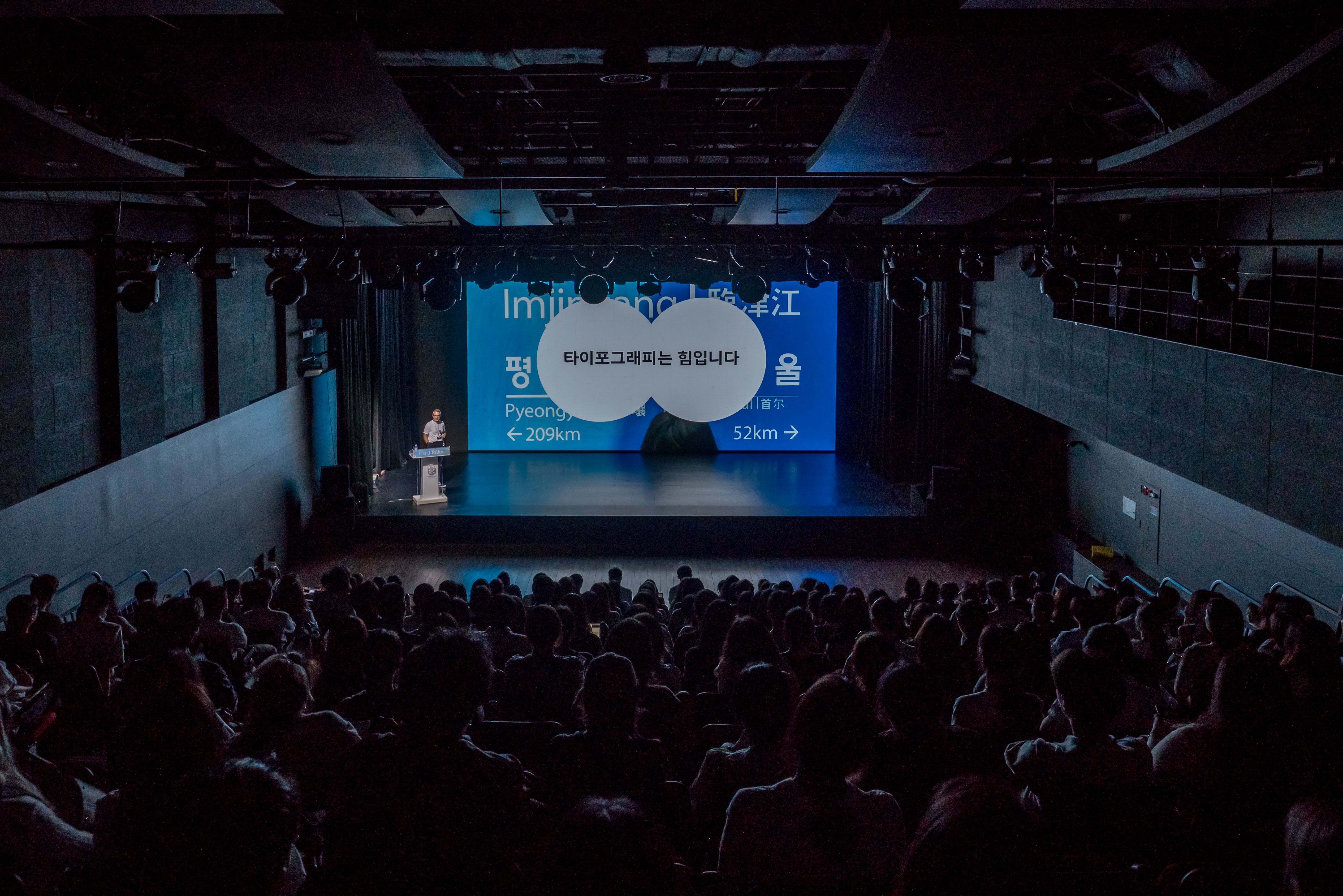
글로벌 폰트 디자인 및 기술 선도 기업 모노타입(Monotype)이 주최한 브랜드톡 코리아 2025(Brand Talks Korea 2025)가 성황리에 막을 내렸다. 7월 31일 서울 가빈아트홀에서 열린 이번 행사는 300명 이상이 참석했으며, 국내외 다양한 업계의 디자이너, 마케터, 브랜드 전략가들이 한자리에 모여 높은 관심과 뜨거운 반응을 이끌어냈다. 이번 행사는 단순한 세미나를 넘어, 브랜드와 타이포그래피의 전략적 가치에 대해 논의하고 인사이트를 공유하는 장이었으며, 국내 타이포그래피 및 브랜딩 분야를 대표하는 전문 세미나로서의 입지를 확고히 했다.
이날 무대에는 세 명의 연사가 올라 브랜드 전략과 경험 설계, 문화적 정체성 구축에 있어 타이포그래피가 어떤 역할을 하는지를 다양한 시각에서 조명했다.
고바야시 아키라(Akira Kobayashi) 모노타입 크리에이티브 타입 디렉터는 40년 가까운 경력을 지닌 세계적인 서체 디자이너로, 독일의 서체 디자이너 헤르만 차프(Hermann Zapf)와 스위스의 아드리안 프루티거(Adrian Frutiger)와의 협업으로도 잘 알려져 있다. 오랜만에 한국을 찾은 그는 글자 형태 자체가 메시지를 전달하는 힘을 다양한 브랜드 사례를 통해 설명하며, 소니, 알리바바, 마쯔다 등 굴지의 기업들과 함께한 서체 개발 경험을 바탕으로 글자의 형태가 정보 전달과 브랜드 감성에 어떻게 영향을 미치는지를 조명했다.
필 가넘(Phil Garnham) 모노타입 수석 크리에이티브 디렉터는 타이포그래피가 단순한 디자인 요소를 넘어 AI와 자동화 시대에 브랜드의 핵심 인터페이스로 진화하고 있음을 강조했다. 그는 ‘타이포그래피는 문화다’라는 메시지를 통해 글로벌 브랜드 사례와 미래 기술을 결합한 인사이트를 공유했다.
앤드류와이어스 브랜드 컨설팅 랩의 김해경 대표는 전략적 브랜딩 관점에서 브랜드 가치 설계와 경험 디자인의 중요성을 강조했다. 그는 브랜드 페르소나와 핵심 가치, 그리고 서체를 통해 브랜드의 철학과 정체성을 물리적으로 구현하는 과정을 통찰력 있게 풀어냈다.
현장에서는 활발한 질의응답 시간도 이어졌다. 참석자들은 연사들과 직접 소통하며 실무에서의 고민과 인사이트를 공유하고 새로운 영감을 얻는 시간을 가졌다.
모노타입코리아 마케팅 총괄 김근원 실장은 “이제 많은 브랜드들이 타이포그래피를 단순한 디자인이 아닌 전략적 자산으로 인식하고 있다”며, “모노타입의 브랜드톡은 그런 변화의 중심에서 목소리를 내는 플랫폼으로 성장해 가고 있다”고 전했다.